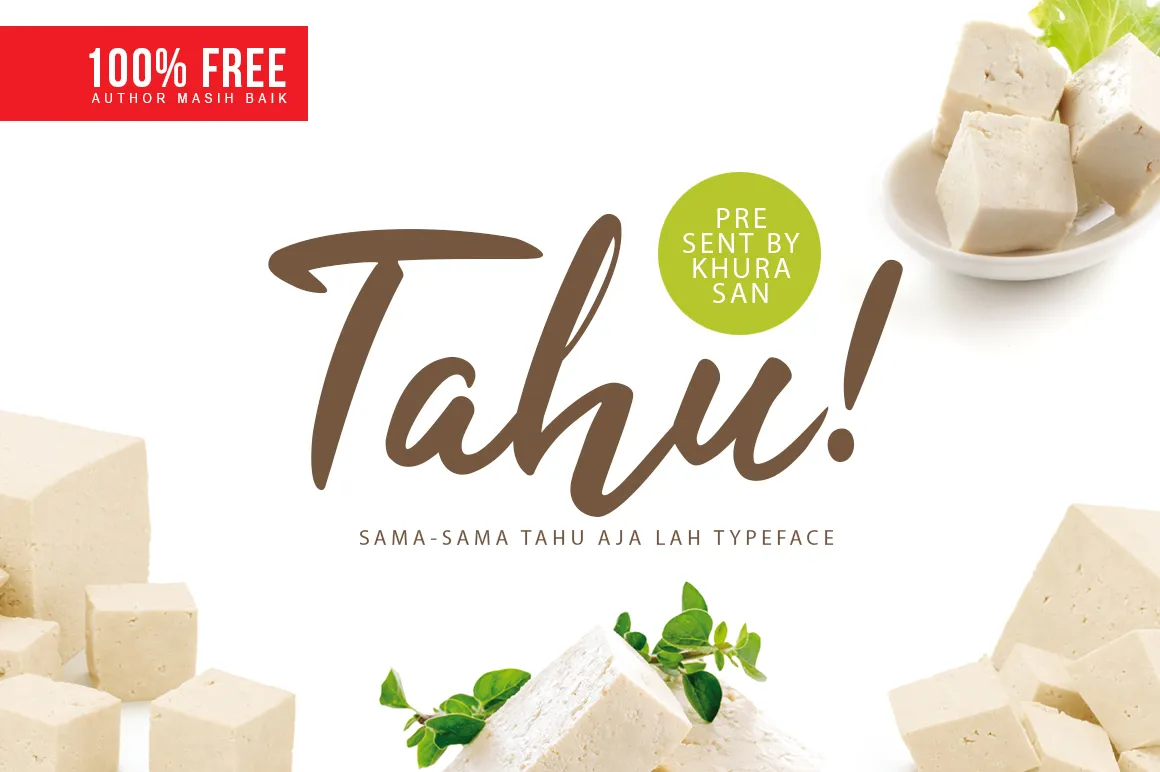
Tahu! Script Font – Fonte Grátis
Tahu! Script Font
A Tahu! Script Font é uma tipografia criada pelo designer khurasan para designers, bloggers, instagramers, youtubers, amantes do estilo de vida moderno e apaixonados por design fresco. Esta fonte é perfeitamente adequada para qualquer tipo de design contemporâneo como banners publicitários, cartões modernos, convites, anúncios, designs sazonais, promoções nas redes sociais, desenhos para a web e estilização de marcas e logotipos. A Tahu! oferece um estilo elegante e sofisticado que se ajusta perfeitamente a esses formatos de design moderno, tornando-a uma escolha ideal tanto para designers experientes quanto iniciantes. Sempre procurando trazer algo novo ao seu trabalho de design, a Tahu! Script é o tipo certo para quando você está em busca de uma fonte única e fresca que enriqueça sua criação.